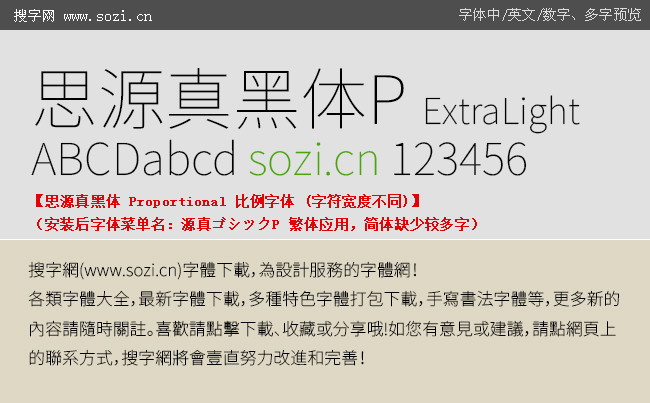
思源真黑體P-ExtraLight
搜字網(wǎng)給大家提供一款思源真黑體P-ExtraLight中文字體下載,思源真黑體字體是源于Google的開(kāi)源字體思源黑體,保留了思源黑體原版的優(yōu)雅以及高可讀性的特色,并在思源黑體的基礎(chǔ)上做出了變化,使得整套字體看起來(lái)更加銳利清晰。適用于適用于大量文字閱讀顯示、代碼編程、排版、打印等應(yīng)用。